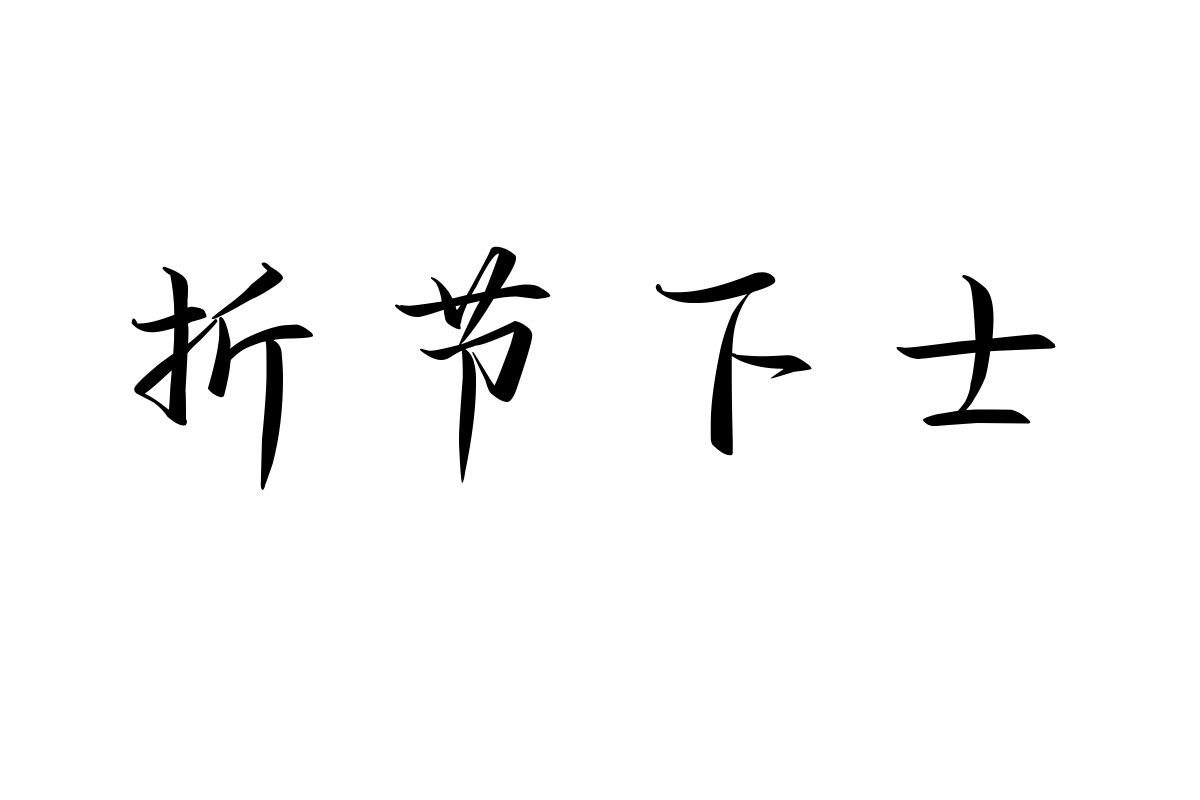
也字工厂侠客行是一款具有独特风格的字体,它以简洁、明快的线条勾勒出侠客的形象,给人一种灵动而不失稳重的感觉。这款字体适用于各种需要强调侠客形象的场景,如游戏、广告、设计等。
也字工厂侠客行字体的特点如下:
1. 线条流畅:这款字体的线条流畅自然,没有过多的装饰,使得整体效果更加简洁明了。
2. 结构清晰:每个笔画都经过精心设计,使得整个字体的结构清晰易懂,易于识别。
3. 风格鲜明:这款字体的风格独特,具有很强的辨识度,能够迅速吸引观众的注意力。
4. 适用范围广泛:无论是用于游戏角色设计、广告宣传还是其他需要突出侠客形象的场景,这款字体都能发挥出其独特的魅力。
总的来说,也字工厂侠客行字体是一款非常适合用来表现侠客形象的字体,无论是从视觉效果还是实用性方面,都值得一试。